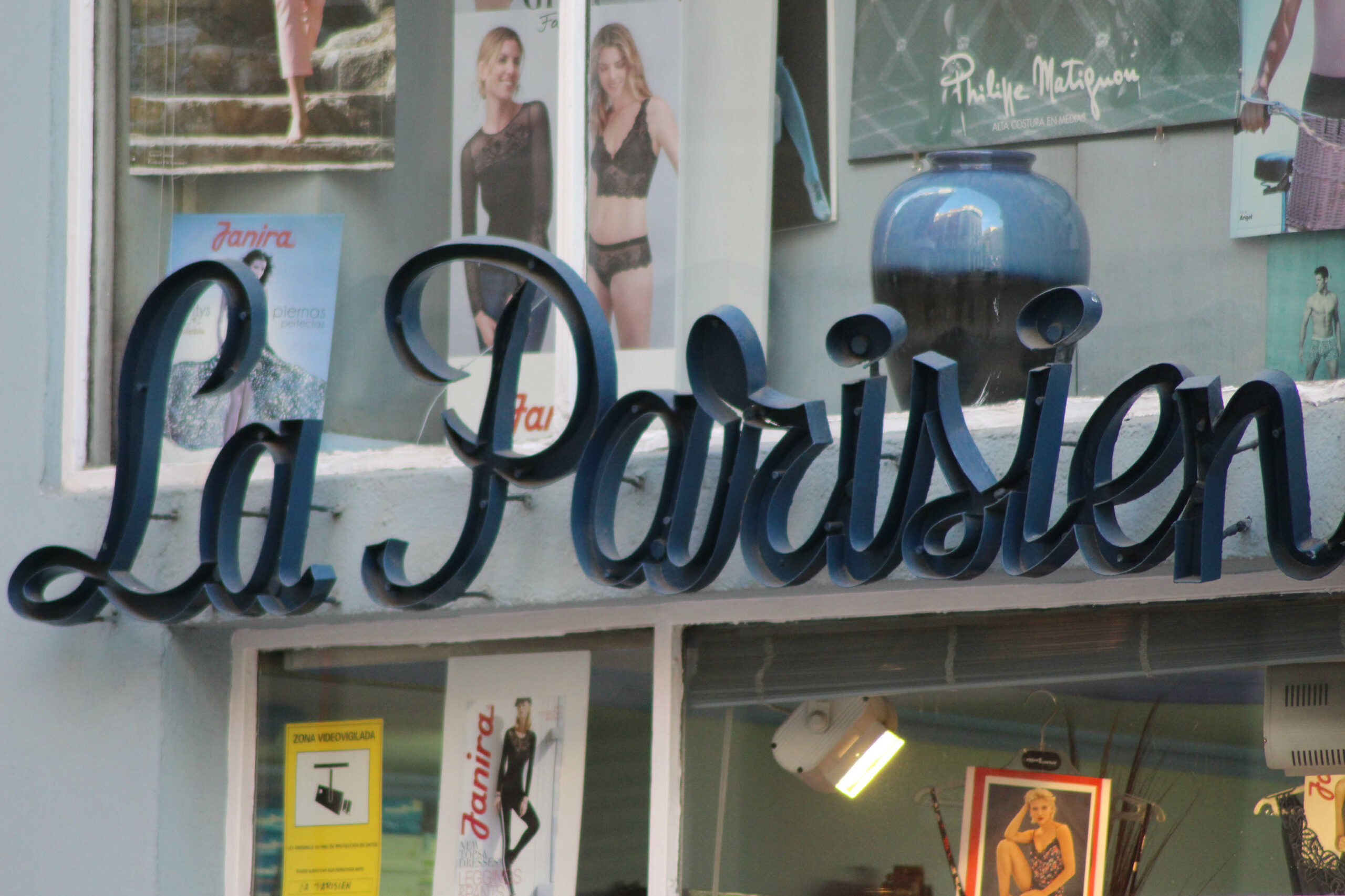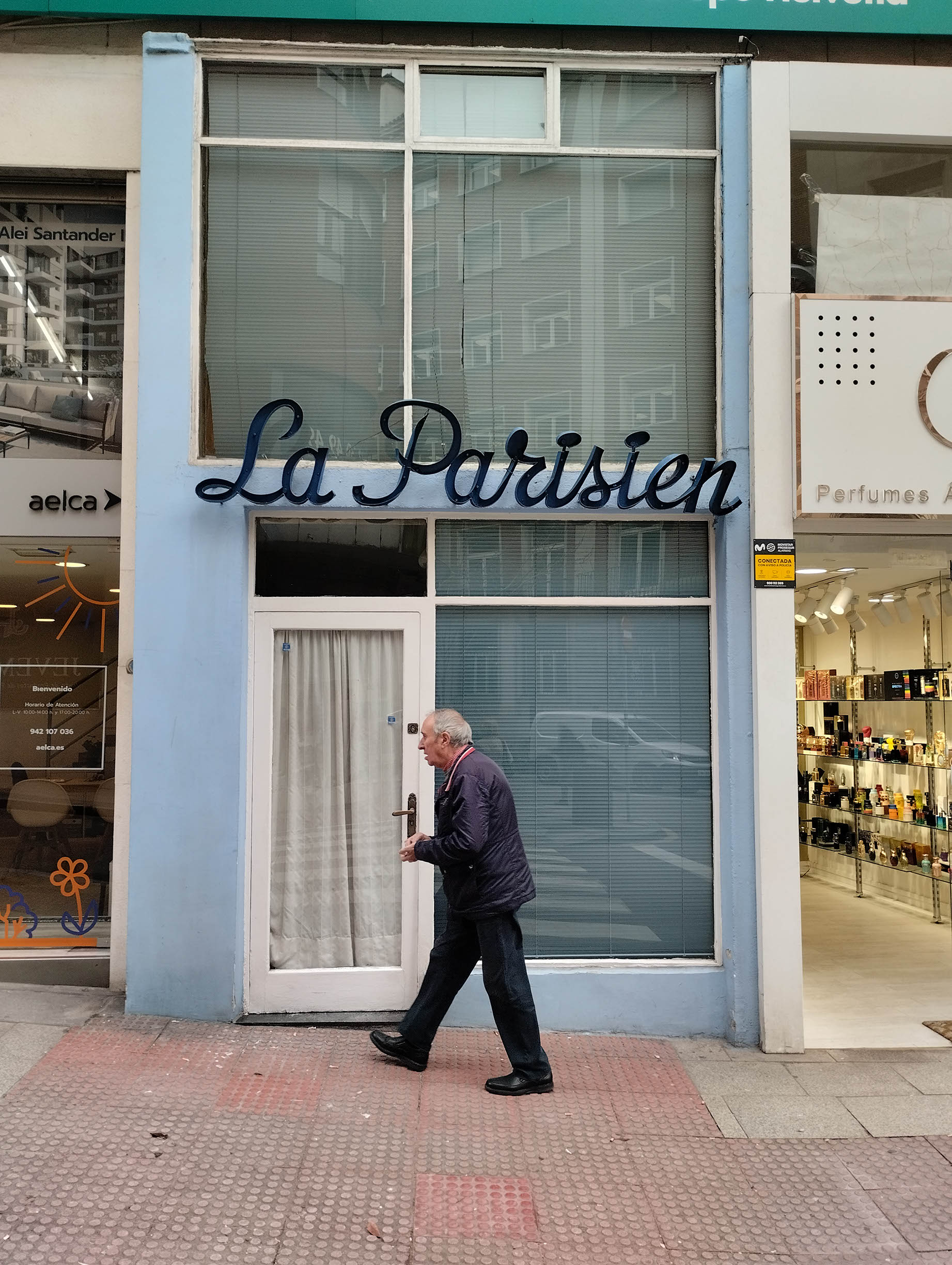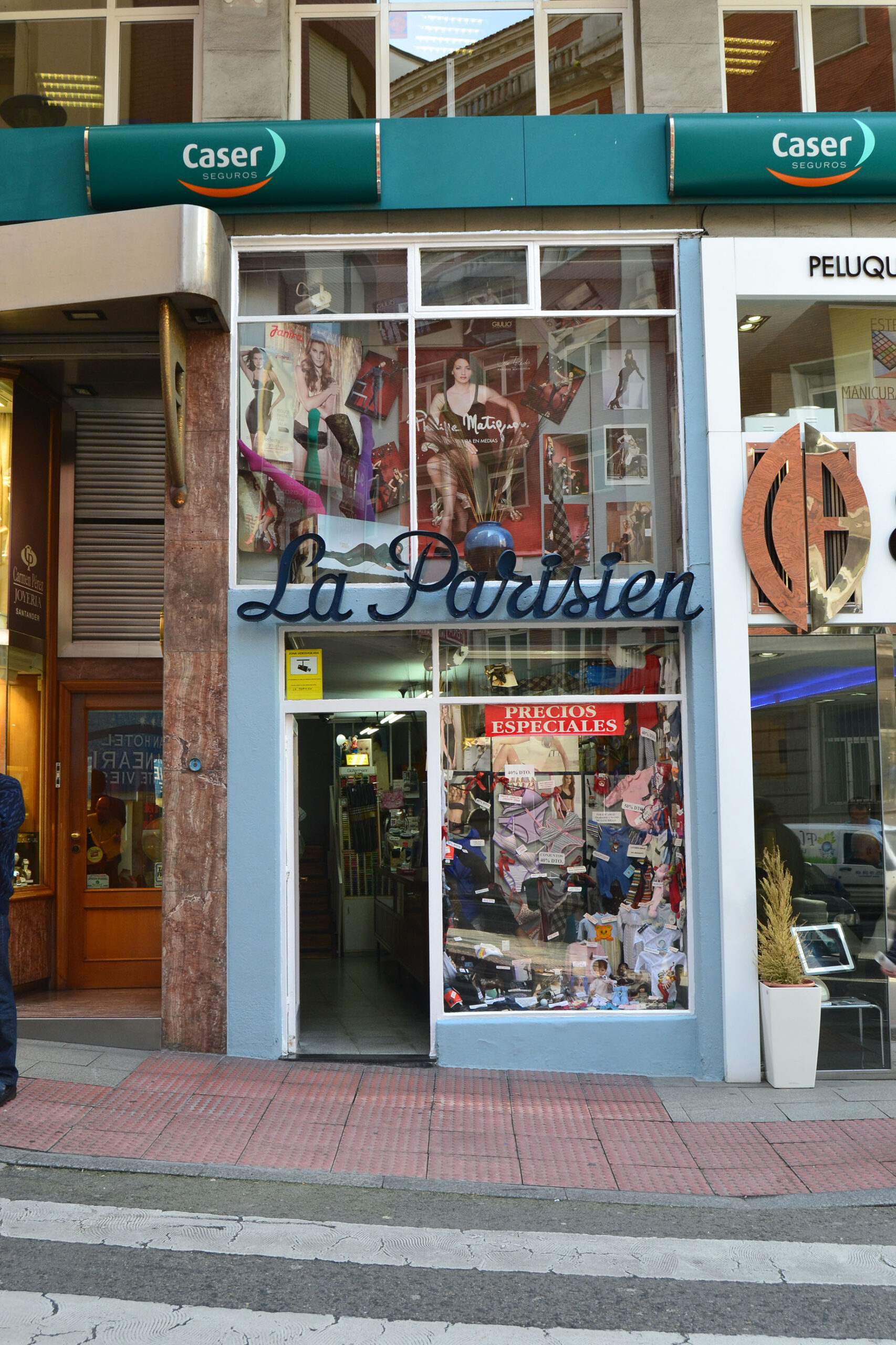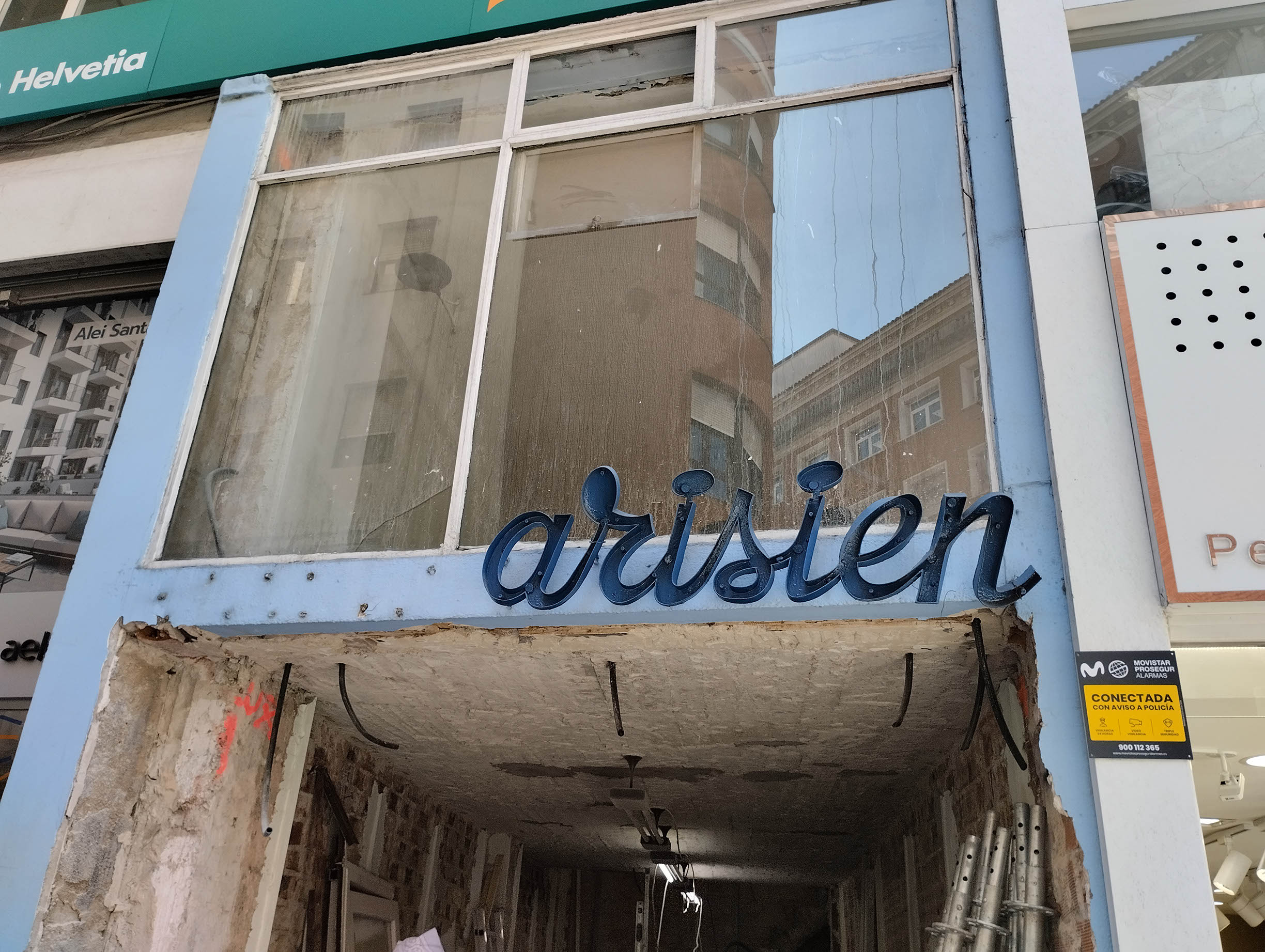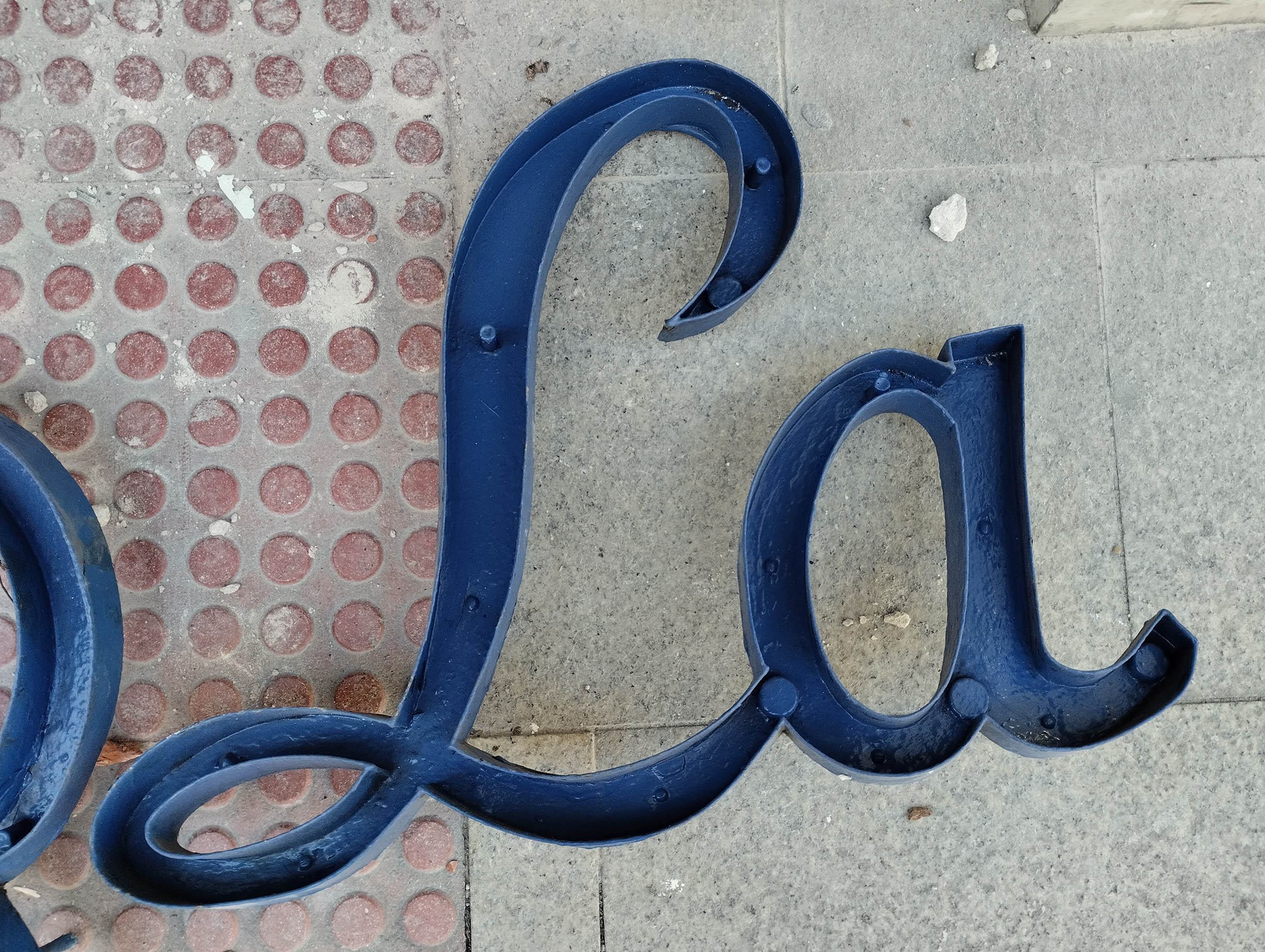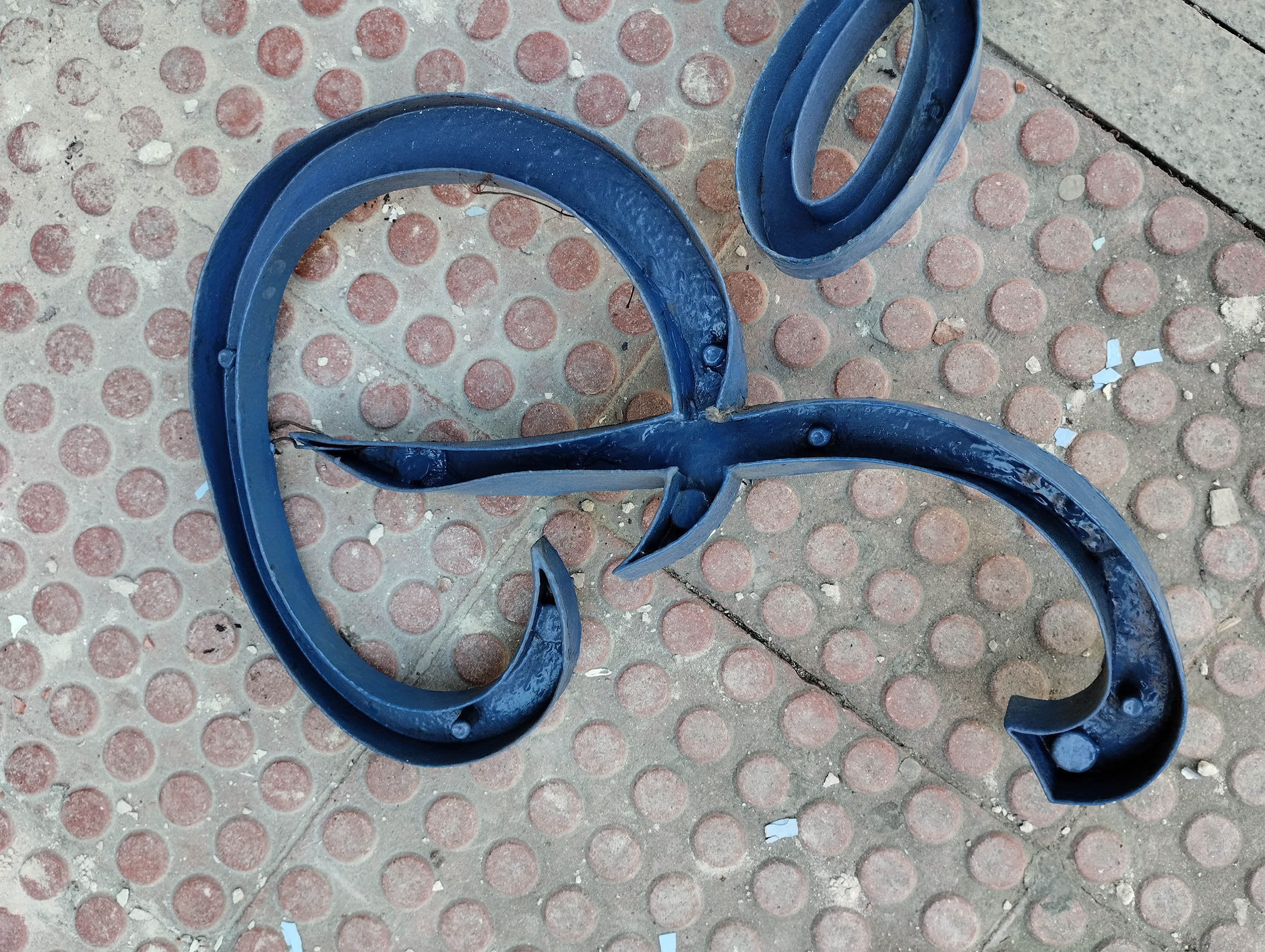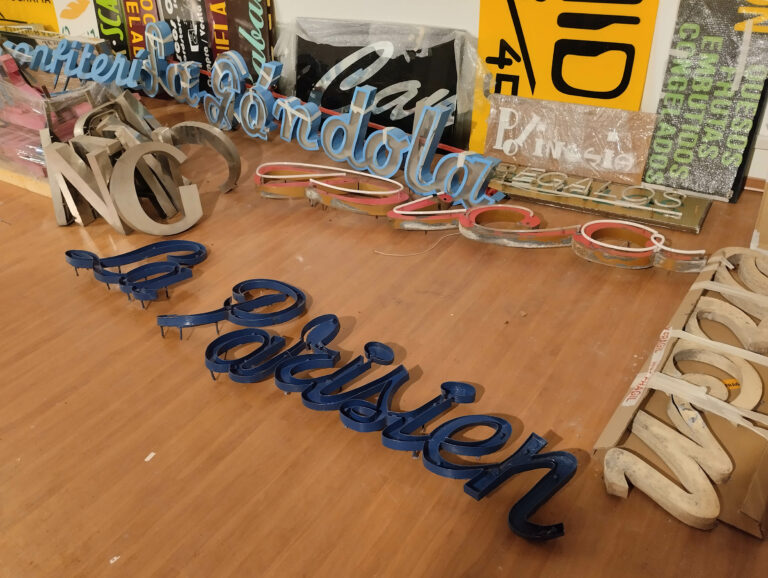
El pasado 6 de abril de 2026 hemos recogido gracias a los operarios que están haciendo la obra, el rótulo de “La Parisien” una de las tiendas más antiguas de Santander ya que se fundó a finales del siglo XIX; tras su cierre en febrero de 2026 después de 130 años activo, Joaquín Suarez, nos avisó para donarnos el rótulo. Casualmente, fue el primer rótulo que se mostró cuando se inició el proyecto en las redes sociales al no haber aún web, en 2014.
Sobre el rótulo
El rótulo data de inicios de los años 60 cuando la tienda se trasladó desde el Edificio SEPI en la Plaza del Ayuntamiento a su ubicación en la calle Ruamayor. Es de metal y esta preparado para instalar los tubos de neón en su interior. Su tipografía es única, en un formato script que nos permite disfrutar de esas curvas y formas de fantasía.
Sobre el comercio
Como se ha dicho este comercio es histórico porque hasta su cierre fue el más antiguo de Santander en activo. Fundado en 1896 por Josefina Mendiazabal, proveniente de Francia tras pasar por el exilio en las Guerras Carlistas, se instaló en la calle San Francisco. Junto a esta abrió la tintorería “La Francesa”; ambos negocios serían regentados por sus hijas. Durante unos años funcionando se pasa a lo bajos del conocido como “Casa SEPI” en la plaza del ayuntamiento, donde estaba el famoso “Gran Bazar” y la “Academia Puente”.  El edificio se derriba en 1963 y los negocios se traslada a distintas ubicaciones; en el caso de “La Parisien” es en Ruamayor hasta hoy.
Edificio SEPI, con «La Parisien» marcada dentro del cuadro.
La gestión de este ha sido íntegramente familiar por las distintas generaciones, siendo Joaquín el último de la saga y el que ha bajado la persiana.
Por fortuna, gracias a la hemeroteca por un lado y a la memoria de la familia por otro, más el rescate físico de este icónico rótulo, aunque la tienda física ya no esté en nuestras calles, la podremos conservar en su totalidad.